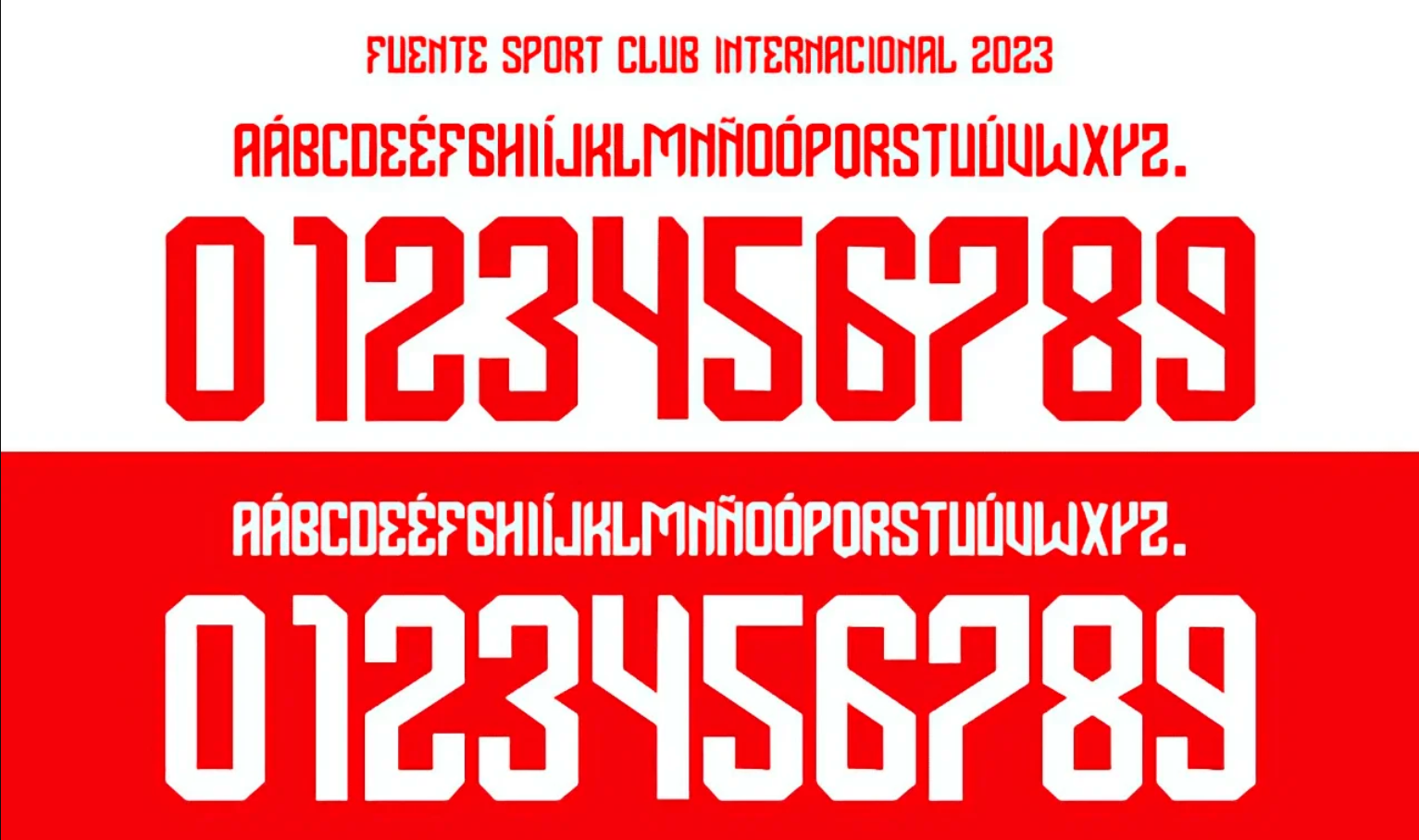
O orgulho de ser Colorado se reflete em cada detalhe do uniforme, e a tipografia é fundamental para manter a autenticidade do manto. A temporada 2023 marcou mais um ano da parceria entre o Internacional e a Adidas, trazendo uma numeração moderna e limpa que se destaca no vermelho vibrante do Beira-Rio.
Estilo Visual e Identidade
A fonte utilizada pela Adidas na temporada 2023 para o Internacional aposta em um visual sólido e funcional. Diferente de tipografias retrô, este estilo privilegia a legibilidade à longa distância, essencial para as transmissões de TV e visibilidade em campo.
Os caracteres possuem espessura média e cantos levemente arredondados internamente, mas com extremidades retas, conferindo um ar tecnológico e contemporâneo. No uniforme titular (vermelho), a aplicação é feita tradicionalmente em branco, enquanto no uniforme reserva (branco), utiliza-se o vermelho, criando o contraste clássico que a torcida ama.